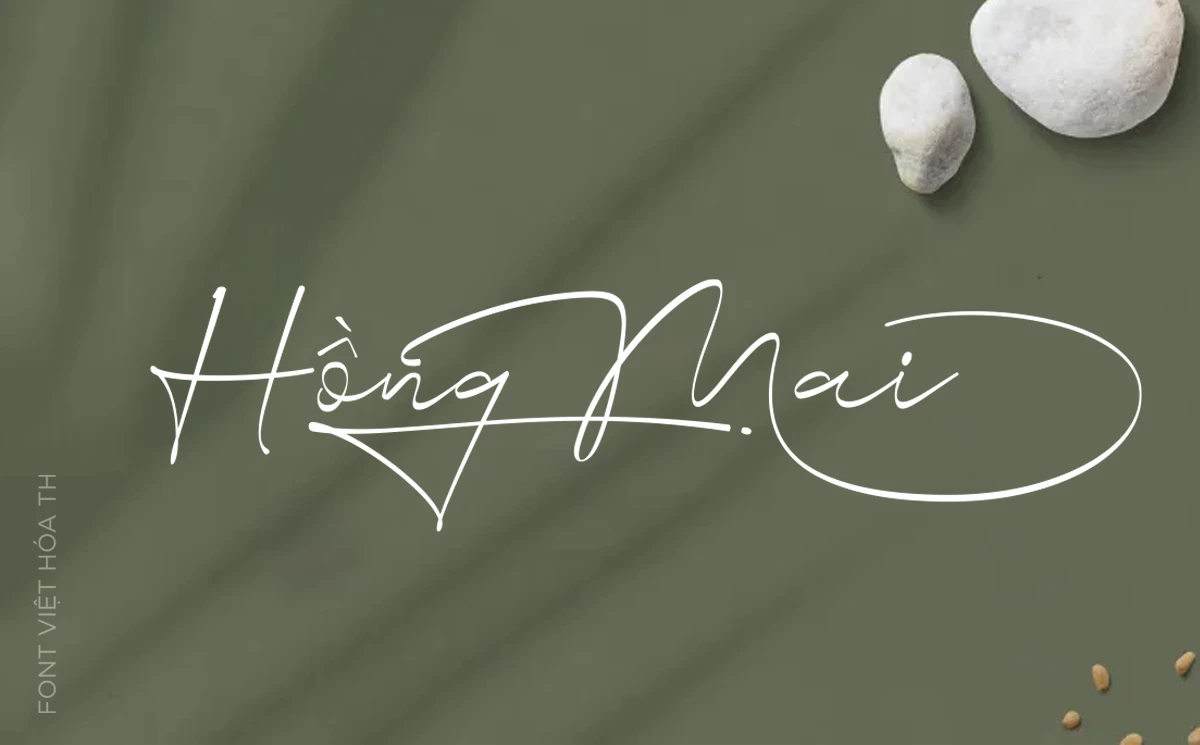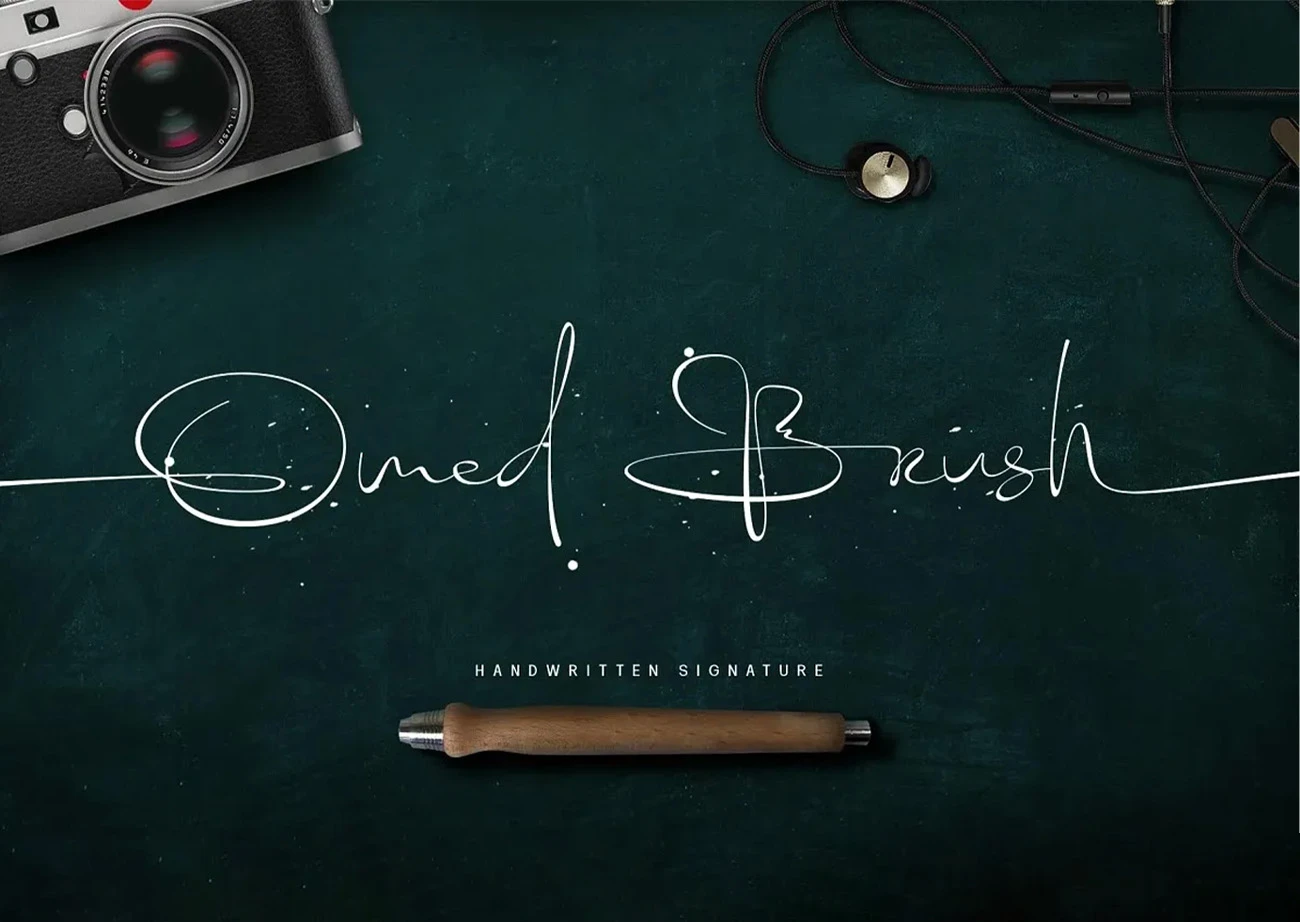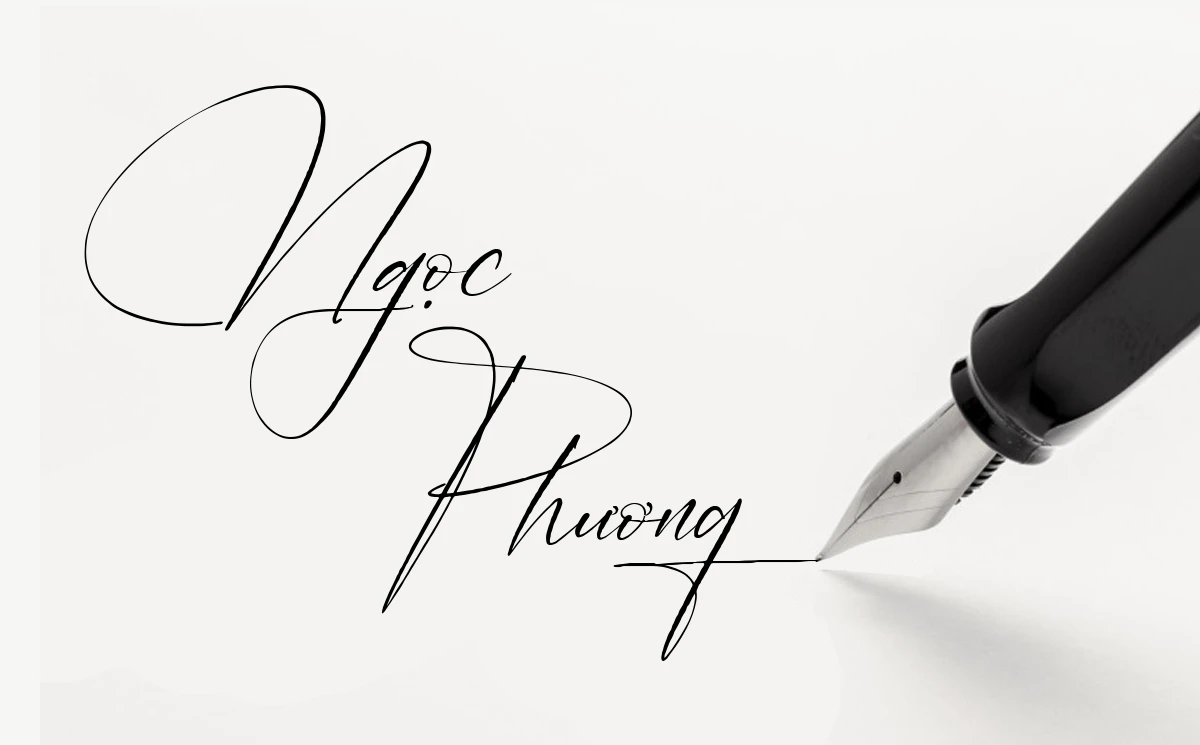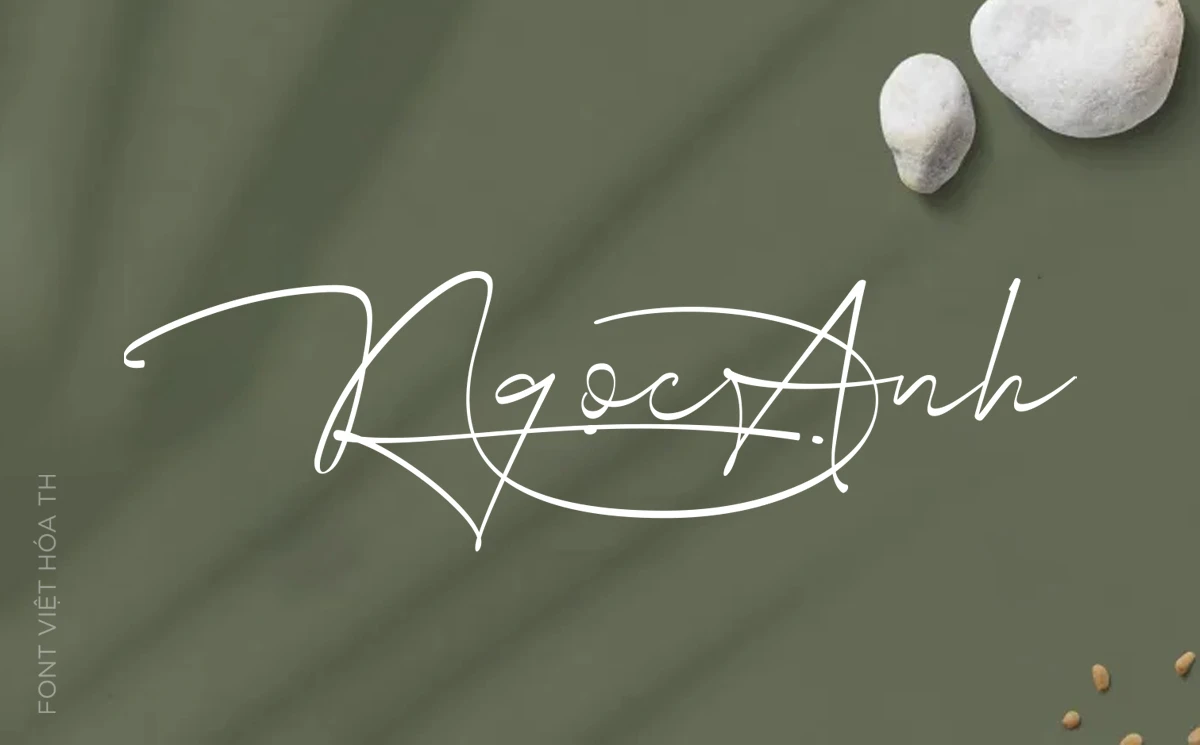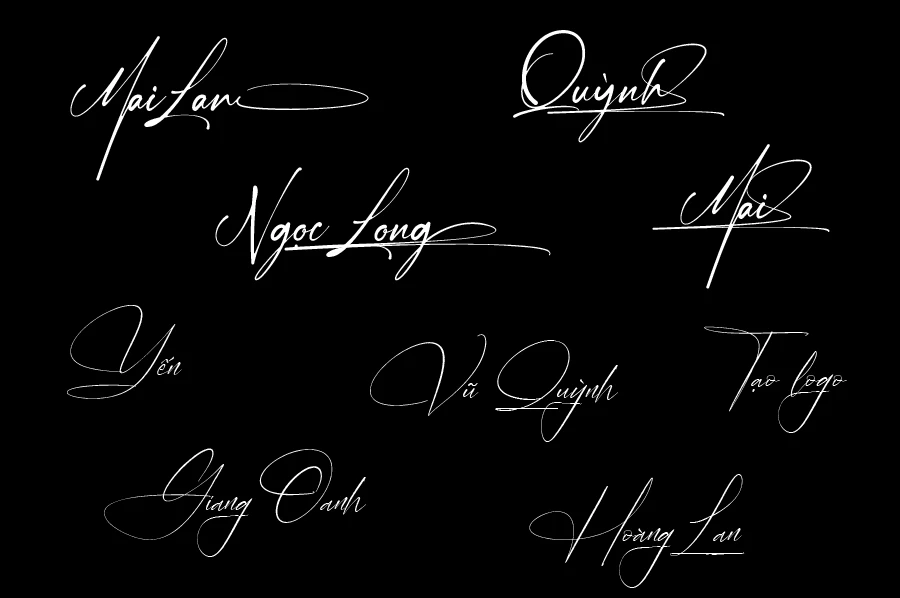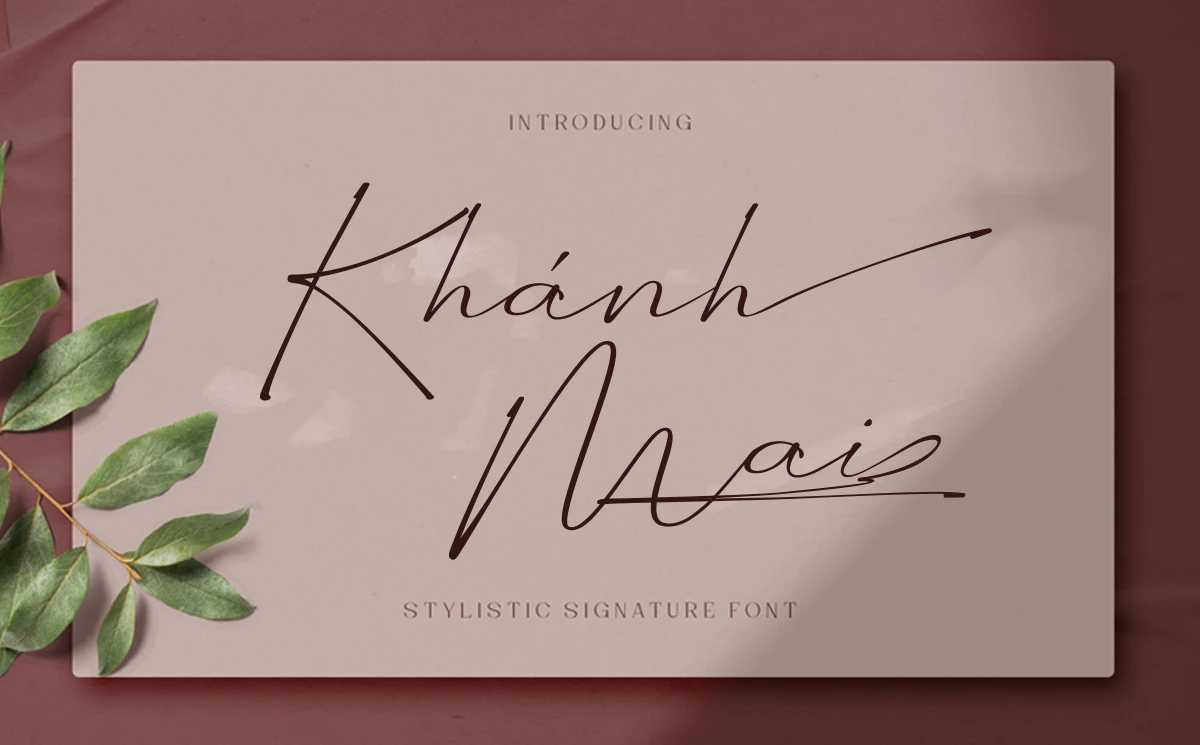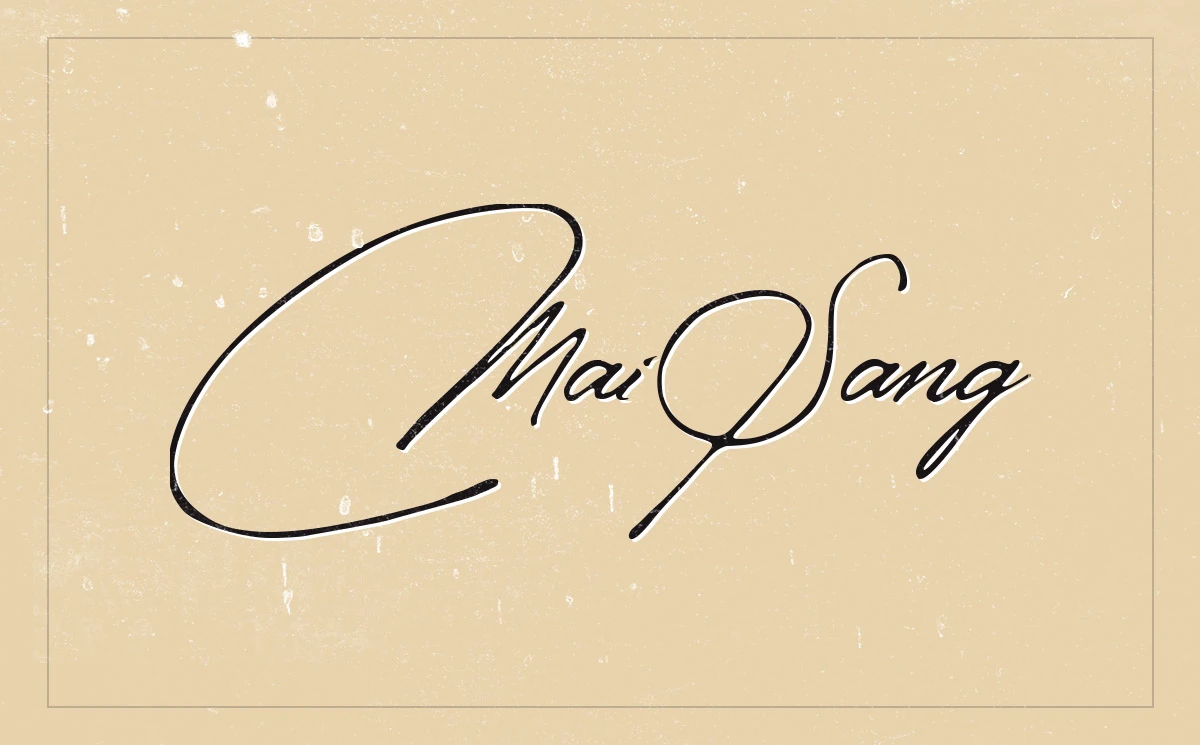
Khám Phá Font Chữ Ký Việt Hóa Độc Đáo
Trong lĩnh vực heloo88 đồ họa, font chữ không chỉ đơn thuần là những ký tự được sắp xếp để hình thành từ ngữ. Mỗi font chữ, đặc biệt là font chữ ký, mang trong mình một phong cách, cá tính và thông điệp riêng cần truyền tải. Những nét uốn lượn đầy nghệ thuật này không chỉ giúp sản phẩm trở nên nổi bật mà còn tạo ra sự gần gũi, thân thiện với người xem. Bài viết này sẽ đi sâu vào khám phá font chữ ký Việt hóa, từ đặc điểm, ứng dụng, cho đến hướng dẫn sử dụng cụ thể. Tải Xuống 15 Font Chữ Ký Đẹp và Việt Hóa Mới Nhất 2024
Font Chữ Ký Là Gì?
Font chữ ký là một loại font được heloo88 nhằm tái hiện vẻ tinh tế của chữ viết tay tự nhiên. Những đường nét trong font chữ này thường mềm mại, uốn lượn và không theo khuôn mẫu, giúp tạo ra sự độc đáo và cá nhân hóa cho từng ấn phẩm. Các font chữ ký không chỉ đơn thuần là một lựa chọn thẩm mỹ mà còn truyền tải cảm xúc, tạo ra sự kết nối với người dùng. Tải Xuống 15 Font Chữ Ký Đẹp và Việt Hóa Mới Nhất 2024
Đặc điểm của Font Chữ Ký
• Phong Cách Chữ Viết Tay Tự Nhiên
- Font chữ ký thường được phát triển để phản ánh đặc điểm tự nhiên của chữ viết tay. Điều này giúp tạo ra cảm giác gần gũi và thân thuộc, khiến người xem dễ dàng tiếp cận hơn với thông điệp mà nó truyền tải.
• Đa Dạng Về Kiểu Dáng
- Có nhiều mẫu font chữ ký khác nhau, từ thanh lịch cho đến mạnh mẽ. Điều này tạo ra sự lựa chọn phong phú cho các nhà heloo88 để phù hợp với ngữ cảnh sử dụng khác nhau, từ thiệp cưới cho đến logo thương hiệu.
• Tính Thẩm Mỹ và Tinh Tế
- Font chữ ký mang lại vẻ đẹp mỹ thuật cao, giúp nâng cao giá trị thẩm mỹ cho các sản phẩm heloo88. Những đường nét mềm mại và tinh tế phù hợp với nhiều dự án đòi hỏi tính chuyên nghiệp và sự sang trọng. Tải Xuống 15 Font Chữ Ký Đẹp và Việt Hóa Mới Nhất 2024
Đặc Điểm Nổi Bật Của Font Chữ Ký
Phong Cách Chữ Viết Tay Tự Nhiên
Font chữ ký như một chiếc cầu nối giao thoa giữa nghệ thuật và văn hóa, giúp người xem cảm nhận được dấu ấn cá nhân qua từng nét chữ.
Đa Dạng Phong Cách
Với các font chữ ký phong phú về kiểu dáng, bạn có thể thoải mái lựa chọn mẫu mã phù hợp với phong cách của từng dự án. Ví dụ:
• Font nhẹ nhàng cho thiệp cưới
• Font mạnh mẽ cho banner quảng cáo
• TH Manchester Signature
Đường nét mềm mại, điềm đạm, thích hợp cho các ấn phẩm cao cấp.
• TH Wellyon
Font chữ hello8862 com với phong cách bay bổng và nhẹ nhàng.
• TH Omaha Beach
Mạnh mẽ và cá tính, lý tưởng cho các ấn phẩm cần được nổi bật.
• TH Nice Memory
Phong cách lãng mạn, thích hợp cho các heloo88 tinh tế.
• TH Corinthiago
Cổ điển, sang trọng, phù hợp cho heloo88 thương hiệu.
• TH Migratory
Nhẹ nhàng và thư giãn, phụ trợ cho heloo88 thương hiệu.
• TH Maistoray
Đầy nghệ thuật, lý tưởng cho các sản phẩm cao cấp.
• TH Mrattoos
Phong cách phóng khoáng, lý tưởng cho các heloo88 trẻ trung.
• TH Alessa Beilaire
Cổ điển nhưng vẫn hello8862 com, mang lại vẻ chững chạc cho các ấn phẩm.
• TH Jalliya
Sáng tạo, với các đường nét độc đáo.
• TH The Billion
Tinh tế và thanh lịch, lý tưởng cho thiệp mời.
• TH Molahesta Italic
Nét chữ nghiêng, nổi bật cho các dự án sáng tạo.
• TH Omed Brush
Đầy cá tính, phù hợp cho các sản phẩm mang đậm dấu ấn cá nhân.
• TH Nice Persona
Đường nét mềm mại, tạo nên vẻ đẹp dịu dàng cho heloo88.
• TH Wellyon
Aminh hello8862 com và thanh thoát, thích hợp cho logo thương hiệu. Tải Xuống 15 Font Chữ Ký Đẹp và Việt Hóa Mới Nhất 2024
Ứng Dụng Của Font Chữ Ký Trong Thiết Kế
Tạo Chữ Ký Điện Tử
Với tốc độ phát triển của giao dịch điện tử ngày nay, font chữ ký là công cụ hiệu quả để tạo ra chữ ký điện tử. Việc sử dụng font chữ ký không chỉ giúp tăng tính chuyên nghiệp mà còn tạo dấu ấn cá nhân cho người sử dụng.
Thiết Kế Logo và Thương Hiệu
Font chữ ký giúp thương hiệu nổi bật với nét chữ linh hoạt, ấn tượng. Khi sử dụng trong heloo88 logo, chúng sẽ tạo ra sự gần gũi, dễ ghi nhớ đối với người tiêu dùng.